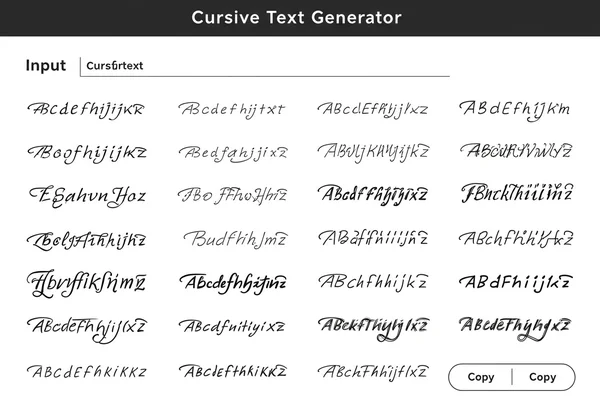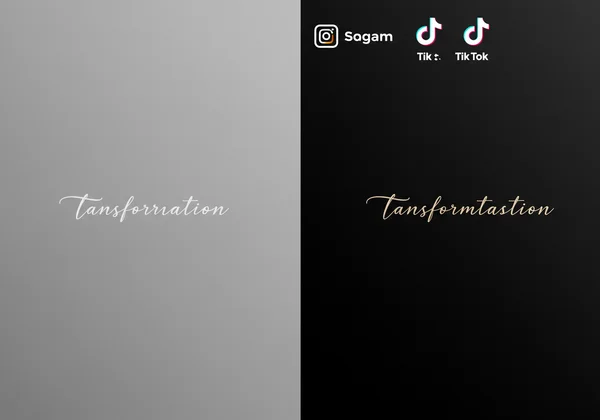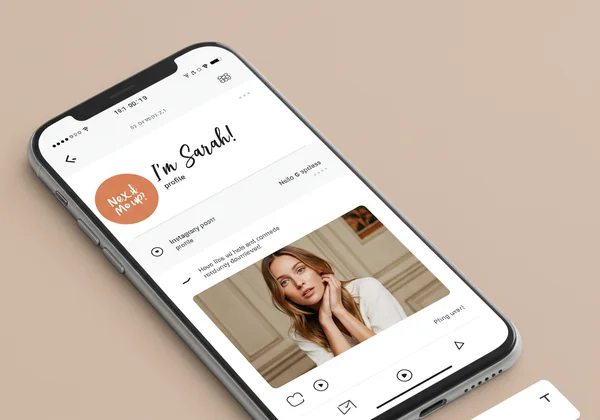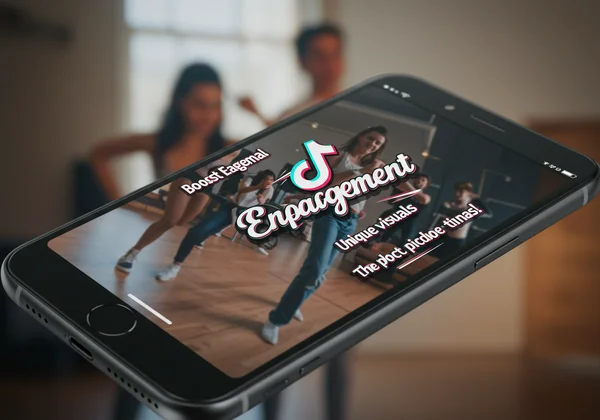
花体字生成器:Instagram 和 TikTok 的花体字体
还在为 Instagram 和 TikTok 上单调的字体感到厌倦吗?是否曾想过 如何将文字设置为花体 以真正脱颖而出?想象一下,用引人入胜、个性化的 花体字 来转换您的个人资料、标题和快拍,轻松吸引眼球并展示您的独特风格。最棒的是什么?您无需成为设计专家或下载复杂的应用程序。我们的 花体字生成器 使您能够即时轻松地创建 花体字,让您的在线形象真正令人难忘。准备好焕新您的内容了吗?轻松生成花体字!
文字从普通字体转换为优雅花体字在屏幕上的效果
如何为 Instagram 获取 花体字体
Instagram 注重视觉吸引力,而您的文字在吸引注意力方面起着至关重要的作用。标准字体可能显得普通且缺乏创意。但有了 花体字体,您可以为您的帖子、评论和私信注入个性和优雅。从精致的艺术字体到俏皮的手写风格,总有一款 花体字生成器 等着您来匹配您的风格。
用 美学花体字 提升您的 Instagram 个人简介
您的 Instagram 个人简介是黄金地段——它是人们访问您个人资料时首先看到的内容!用完美契合您品牌或个性的 美学字体 让它令人难忘。一个独特的花体名字或用优美脚本写成的吸引人简介,可以立即让您更具辨识度。与其写“你好,我是 Sarah”,不如想象一下“𝓗𝓮𝓵𝓵𝓸, 𝓘'𝓶 𝓢𝓪𝓻𝓪𝓱!” 这一简单的改变可以立即让您的个人资料更具记忆点,吸引那些欣赏您独特风格的新粉丝。要为您的个人简介进行彻底的改头换面,请尝试我们的个人简介字体工具并见证奇迹的发生。
Instagram 个人资料显示花体个人简介和带有花体标题的帖子
为 Instagram 标题和快拍增加亮点
除了您的个人简介,Instagram 字体生成器 工具也非常适合美化您的标题和快拍。精心挑选的 Instagram 花体字 可以强调关键信息,为照片增添一丝浪漫,或使号召性用语更具吸引力。可以考虑使用 脚本字体生成器 风格来:
• 帖子标题:突出特殊时刻或引言。
• 快拍文字:创建具有视觉吸引力的投票、提问或公告。
• 评论和私信:为您的互动增添个性化触感。
关键在于有策略地使用这些字体来增强可读性和视觉趣味性,而不是削弱它们。尝试不同的风格,看看什么最能引起您的内容和受众的共鸣。不要让您的创造力受限于标准字体;探索我们多样化的选项,轻松创建引人入胜的标题!
让您的 TikTok 文字 脱颖而出
TikTok 依赖于创意和快速吸引眼球的内容。如果您的视频文字与其他人的融为一体,那么您就错失了一个脱颖而出的绝佳机会。利用 TikTok 字体 添加独特的视觉效果,可以使您的视频更具分享性,并使您的个人资料更具吸引力。
独一无二的 TikTok 个人资料和视频文字 花体字
与 Instagram 一样,您的 TikTok 个人资料将从自定义的 花体名字生成器 或独特的简介中受益匪浅。想象一下拥有一个立即引人注目的 ID!当涉及到视频文字时,添加 花体字生成器 风格可以:
• 强调关键词:让重要信息脱颖而出。
• 增加个性:选择一种 手写字体生成器 风格以增加个人触感,或选择一种粗体脚本以增强高能量感。
• 提高参与度:独特的视觉效果通常会带来更多的分享和评论。
无论您是创作教程、舞蹈挑战还是讲故事视频,自定义的 TikTok 字体 都能将您的内容从优秀提升到卓越。不要满足于一成不变的外观;开始使用 TikTok 字体并让您的视频真正令人难忘。
TikTok 视频帧带有动画花体文字叠加
最大化 TikTok 曝光度的技巧
虽然独特的字体能让您的内容看起来很棒,但巧妙的策略能让它被看到。以下是一些在使用 TikTok 花体字体 时最大化曝光度的技巧:
• 一致性:如果您正在建立品牌,请考虑坚持使用几种标志性的花体风格。
• 可读性:确保您选择的字体仍然易于阅读,尤其是在小屏幕上。
• 行动号召:使用醒目的花体字来表达“链接在个人资料中!”或“关注获取更多!”等短语。
• 结合热门趋势:将热门音效和挑战与您独特的字体选择相结合,以获得强大的效果。
通过周到地应用这些技巧,您独特的文字不仅会看起来很棒,而且还将为您的整体内容策略做出贡献,帮助您吸引更多的关注和互动。
复制粘贴字体 背后的魔力
您可能会想,“这些 复制粘贴字体 如果不是真正的字体文件,它们是如何工作的呢?” 这就是 Unicode 的魔力所在,了解它能极大地增强您对这些多功能字符如何在各种平台上运行的信任感。
为什么 Unicode 字体是您的 社交媒体利器
您通过我们的工具生成的“字体”不是需要安装的传统字体文件。相反,它们是来自 Unicode 标准的特殊文本字符。Unicode 是一种通用的字符编码标准,为每个字符提供一个唯一的编号,无论其平台、程序或语言如何。这意味着 花体字书写生成器 创建的不是图像,而是几乎所有现代设备和应用程序都可以显示的实际文本字符。
这就是为什么您可以直接生成文本,复制并将其粘贴到 Instagram、TikTok、Facebook、WhatsApp 或几乎任何其他地方。对于任何想要在不进行技术操作的情况下为在线交流注入独特的 在线形象 的人来说,这都是一个改变游戏规则的功能。探索 Unicode 字体并释放您的创造潜力!
为您的信息选择完美的 花体风格
凭借丰富的 花体字生成器 选项库,选择正确的花体风格对于有效传达您的信息至关重要。考虑上下文和您期望的影响:
• 优雅与正式:适用于邀请函、专业简介或精致的公告。
• 俏皮与异想天开:非常适合休闲聊天、有趣的标题或个人问候。
• 大胆而醒目:适用于标题、行动号召或发表强有力的声明。
• 手写感:带来个人、真实的感觉,类似于 手写字体生成器。
我们的工具允许您即时预览不同的风格,从而轻松找到最适合您 独特风格 的匹配项。不要害怕尝试!完美的字体可以放大您的信息。
您的首选 花体字生成器:即时风格
说到将您的文本转换为令人惊叹的花体字,我们的 花体字生成器 是您终极的、免费的且极其易于使用的解决方案。我们设计的平台直观、快速,并提供丰富的功能来增强您的创造力。
花体字生成器的简单界面,显示输入框
立即转换您的社交媒体形象!
社交媒体上枯燥、通用的文本的日子已经一去不复返了。借助我们的 花体字生成器,您可以通过即时创建引人注目、个性化的 花体字体 来真正反映您的风格并使您的内容与众不同。无论您是目标是病毒式传播内容的社交媒体影响者,寻找快速字体预览的创意设计师,还是只是喜欢在日常消息中添加一抹 创意 的人,我们的 花体字生成器 都是您的首选资源。
不要让您的文字淹没在背景中。提升您的 社交媒体形象,让每个帖子、简介和标题都成为艺术品。访问我们易于使用的花体字体工具并立即开始转换您的文本!
关于花体社交媒体字体的常见问题解答
以下是一些关于在社交媒体上使用花体字体的常见问题:
如何在 Instagram 上使用花体字书写?
要在 Instagram 上使用花体字,只需使用我们的 在线花体字生成器,在输入框中键入您想要的文本,从我们的库中选择一种花体样式,然后点击“复制花体字”。然后,将此独特文本直接粘贴到您的 Instagram 个人简介、标题、评论或私信中。这是增强您的个人资料和帖子的极其简单且免费的方式。
我如何将我的文字设置为花体?
您可以通过使用我们的 在线花体字生成器 轻松地将 您的文字设置为花体。只需键入您的常规文本,选择各种花体样式,然后即时复制转换后的文本。这些是特殊的 Unicode 字符,可在大多数平台和设备上显示为花体,无需安装任何东西。立即将您的文字设置为花体!
如何获取可以复制粘贴的花体字体?
要 获取可以复制粘贴的花体字体,请访问我们的 花体字体生成器。我们的网站专门使用 Unicode 字符将标准文本转换为各种 花体字生成器 样式,包括各种花体选项。生成后,您可以简单地单击复制文本,然后将其粘贴到任何地方——无论是社交媒体、消息应用程序还是数字文档。这些字体旨在提供最大的兼容性和易用性。查找花体字体并开始自定义您的文本!